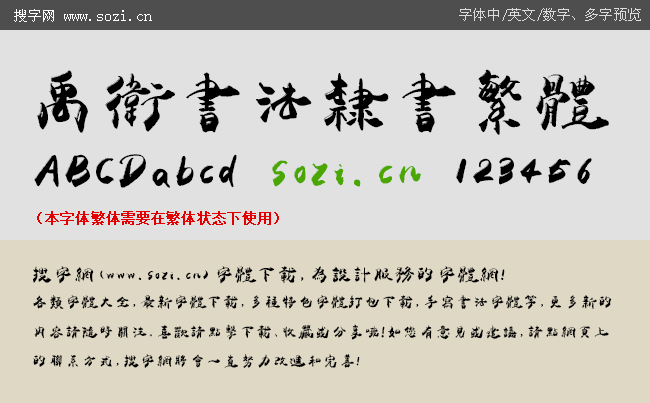
禹衛(wèi)書法隸書繁體
搜字網(wǎng)給大家提供一款禹衛(wèi)書法隸書繁體中文書法字體下載。該字體凝重典雅,古樸莊重,具有濃厚的古典氣息,適合包裝設(shè)計(jì)、海報(bào)設(shè)計(jì)、畫冊(cè)設(shè)計(jì)等廣告設(shè)計(jì)場(chǎng)合使用。